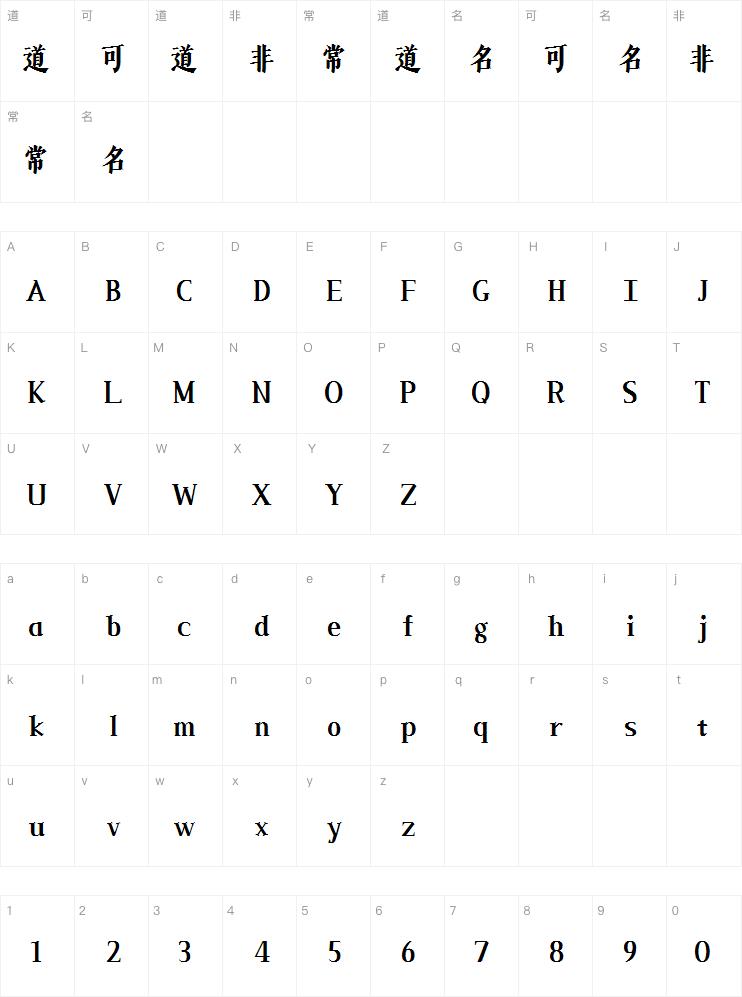
山海江南婉宋95w
山海江南婉宋95W,是一款全新的字体,是山海江南婉宋字体家族系列中的特粗款,编号95W,包含汉字9169个,符号200+个。是由上海拾岁科技有限公司独立设计和制作。该字体是一款国风复古字体,字形融入中国宋代古籍善本之字形特性,宋刻本是中国古籍中最为珍贵的版本之一,素有“一页宋版,一两黄金”的说法,被历代藏书家、学者奉为瑰宝。该字体融入了宋代刻本秀雅端庄,字形瘦高,结构重心偏上,古朴大方,起落顿笔有棱角。该字体采用柳体(柳公权)为基础蓝本,饱有笔墨之意,带有浓厚的书法韵味,笔画顿挫有力,结构严谨,看上去赏心悦目。在秉承笔形间创新,结合当代设计视觉环境,融入现代审美,适用场景更多元,笔画造型清晰锐利,删繁取简,速度感强,端庄秀丽,完美地呈现出该字体的秀美。